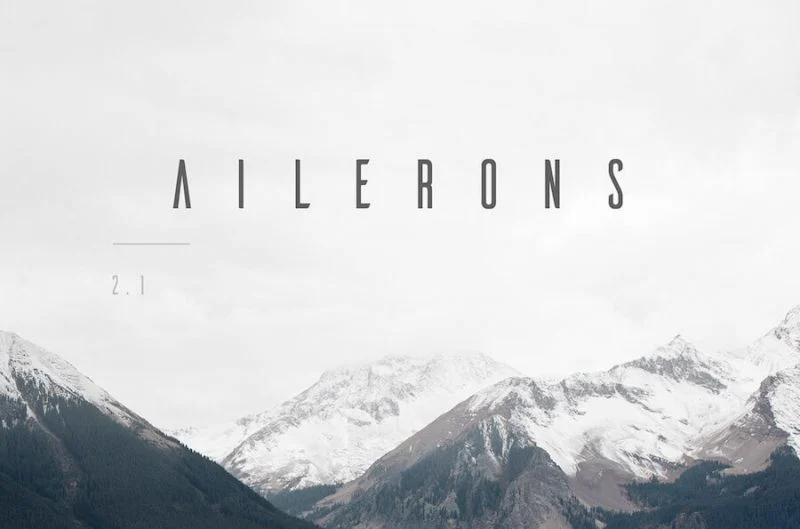
50 melhores fontes de logotipo para seu próximo site
Publicados: 2023-04-27Em pânico com um logotipo incrível que pode expressar e impressionar simultaneamente? Neste artigo, abordamos algumas das melhores opções de fonte de logotipo .
Existe uma grande variedade de fontes especialmente para logotipos que diminuirão sua tensão. Você pode escolher entre a enorme coleção de fontes para criar o logotipo que preferir e ver a mágica.
Como selecionar uma fonte para o seu logotipo?
Antes de começar a criar seu logotipo, um dos fatores mais importantes a considerar é o nicho do seu negócio. Se você estiver no nicho de entretenimento, a fonte será diferente, se você estiver no nicho de ciência ou negócios, a fonte será diferente.
Portanto, a personalidade geral do seu negócio faz uma grande diferença ao selecionar a fonte do logotipo. Além disso, você precisa criar um mapa mental sobre o conteúdo que vai publicar.
Se você criar um logotipo divertido para o seu site enquanto publica um tipo de conteúdo sério, será uma incompatibilidade. Portanto, o logotipo do seu site deve combinar bem com o tema geral do seu negócio.
Então, vamos ver as principais fontes de design de logotipo que você pode usar.
Avestruz Sans
Uma fonte Sans Serif estreita, Avestruz Sans pode ser uma opção de nicho para criar seu logotipo. Ele vem com letras maiúsculas e borda arredondada.
Você obtém essa fonte na versão ultra light, light e bold. Veja como seu logotipo pode ficar com a fonte Ostrich Sans.
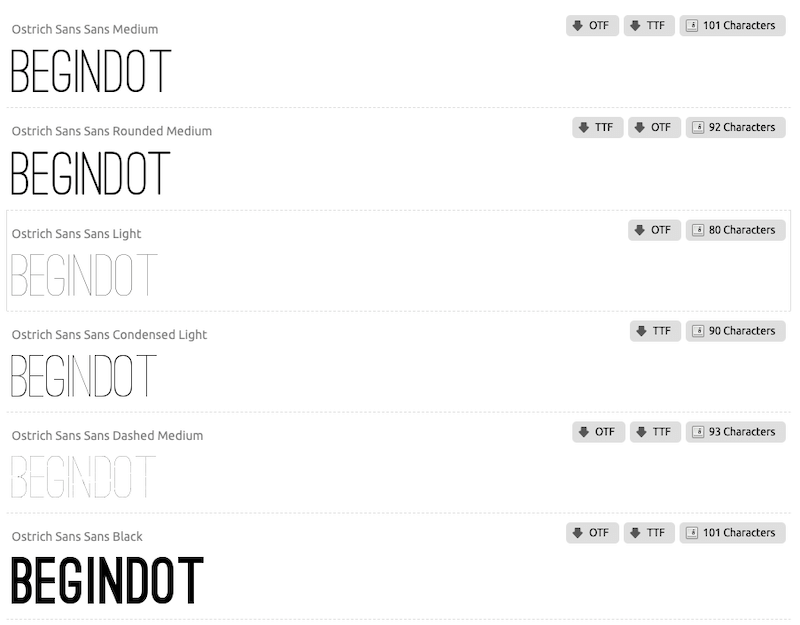
Avanço FF
Desenhado por Evert Bloemsma, o FF Avance é uma boa opção para criar um design de logotipo. Esta fonte suporta mais de 80 idiomas diferentes.
O design serifado assimétrico da fonte a torna diferente de outras fontes.
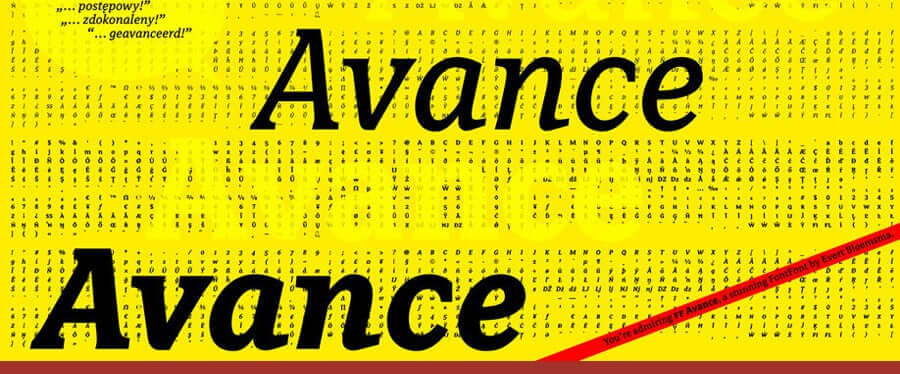
bodoni
A fonte Bodoni é uma combinação de design grosso e fino que a torna uma escolha diferente e interessante para designs de logotipo.
Marcas populares como Vogue e Calvin Klein usam esse tipo de design para o logotipo de sua marca. Você pode baixar e usar esta fonte gratuitamente para qualquer projeto pessoal.
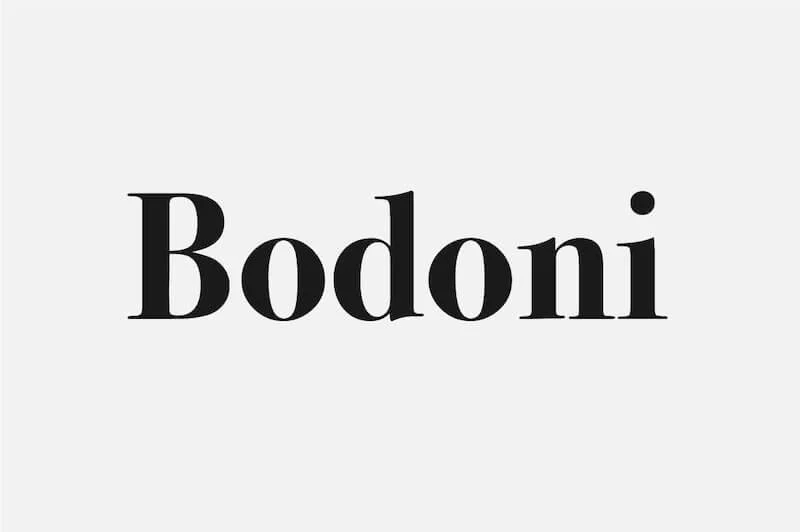
Al Fresco
Projetada por Laura Worthington, essa fonte de logotipo é bastante sofisticada e moderna. A sensação é fresca e emocional.
O sabor da Europa foi bem capturado por esta fonte, e a presença de ligaduras e swashes a tornou ainda mais querida.
De fato, irresistível é a palavra que vem à mente ao descrever essa fonte. A fonte suporta muitos idiomas, do albanês ao zulu, e pode ser comprada ao custo de 23 libras.
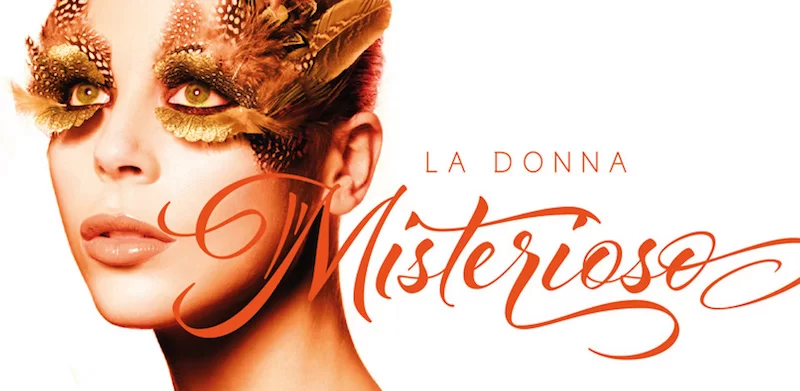
Lombok
Uma fonte elegante para criar seu logotipo. Você pode baixar esta fonte do Behance para criar um logotipo sofisticado para o seu próximo projeto.
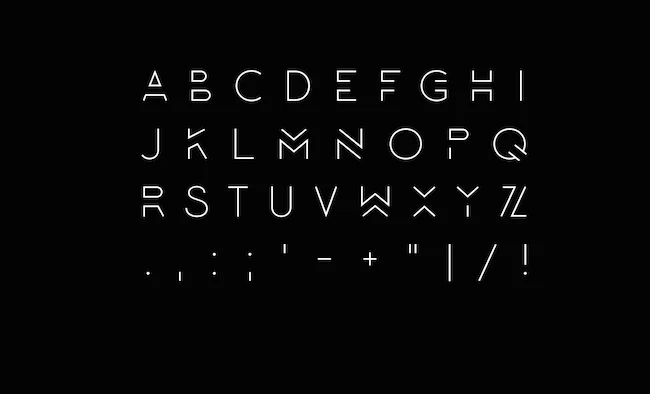
Aracne condensada
Essa fonte encontra seu uso em vários eventos, desde os créditos que rolam após o término de um filme ou a etiqueta de qualquer fantasia. Existem quatro pesos nesta família caracterizada por figuras alongadas, ousadas e dinâmicas.
Está disponível nos estilos regular, condensado e ultracondensado para máxima funcionalidade. Isso foi projetado por Antipixel. A fonte tem oito variações e você pode comprar o conjunto completo por 72 libras. Esta fonte é compatível com PC e Mac.
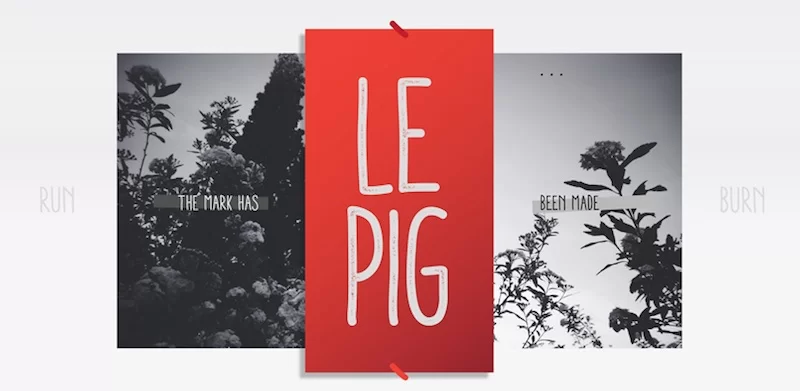
Choplin
Uma bela fonte gratuita criada pela Família Campton. Você pode usar essa fonte gratuitamente e criar um logotipo de ótima aparência para o seu projeto.
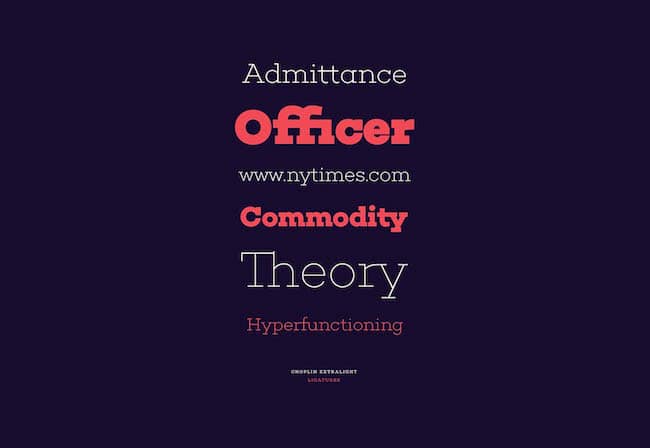
Bela Face37
Face 37 é a mente por trás desta fonte que é ostentada por traços largos e curvas elegantes que dão uma sensação vintage. A beleza de ambos os lugares, Nova York e Paris, são combinadas aqui.
A versão stencil vem com uma abordagem minimalista e possui geometria perfeita. As opções de compra disponíveis para esta fonte são Webfont e Desktop, e o preço é de 25 libras pelo conjunto.
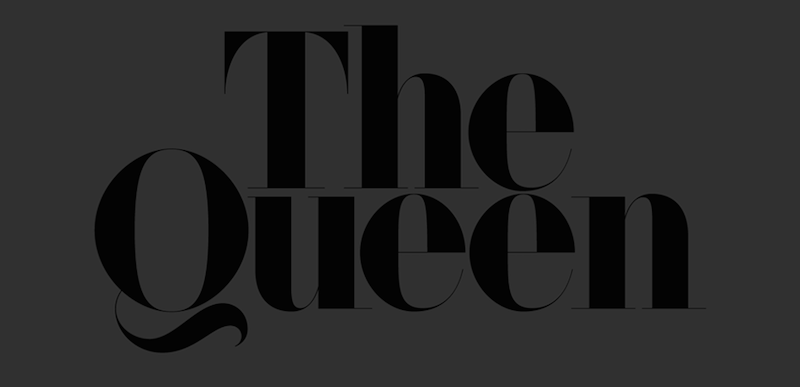
Um dia
Uma fonte de ótima aparência para criar um logotipo sofisticado para seus projetos. A fonte está disponível em diferentes pesos para que você possa usar a versão perfeita que se encaixa perfeitamente no seu projeto.
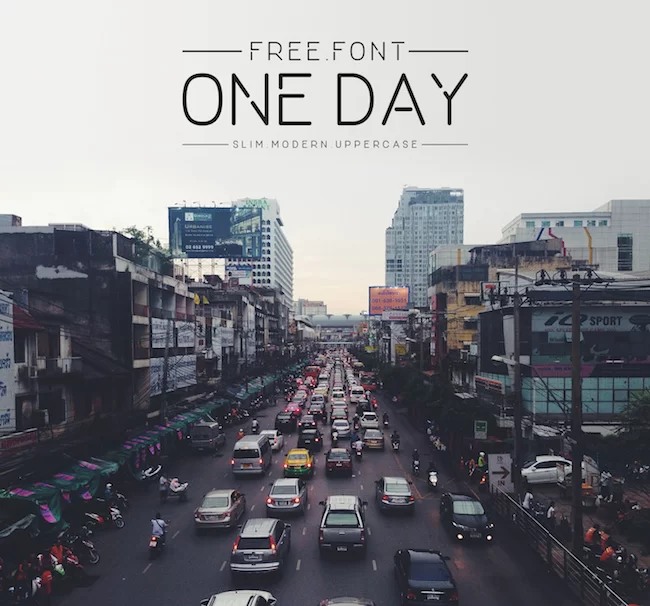
ailerons
Outra bela opção de fonte para criar um design de logotipo moderno e com aparência profissional. Você pode baixar essa fonte do Behance e usá-la para criar seu logotipo.
Várias correções aconteceram em relação a essa fonte e, finalmente, foi escolhida uma versão final legível e lucrativa. O preço é de $ 24 cada e $ 86,80 para todo o grupo.
Nota Final
Se você pesquisar adequadamente por fontes de logotipo, será mimado pelas escolhas, pois há inúmeras opções e, portanto, navegue por essas trinta fontes e escolha a fonte que expressa sua ideia e tem o melhor sabor.